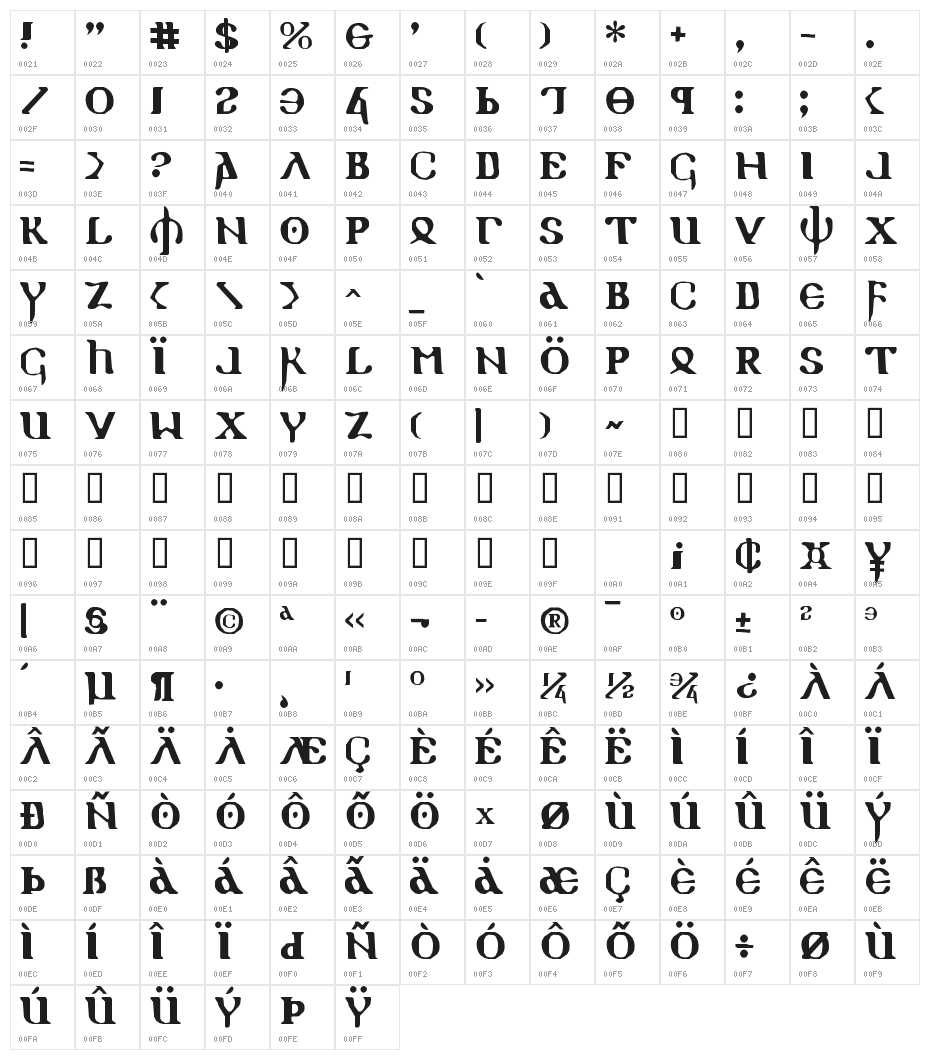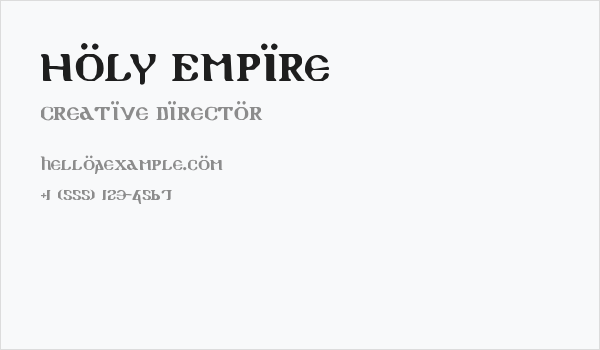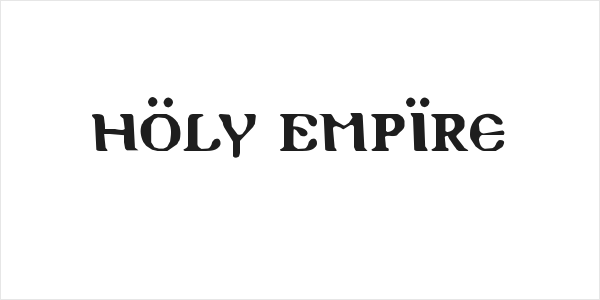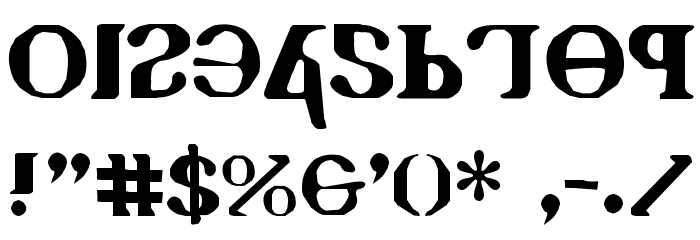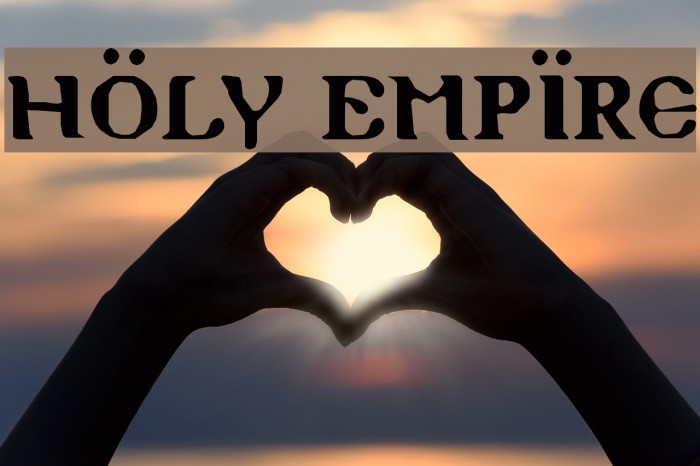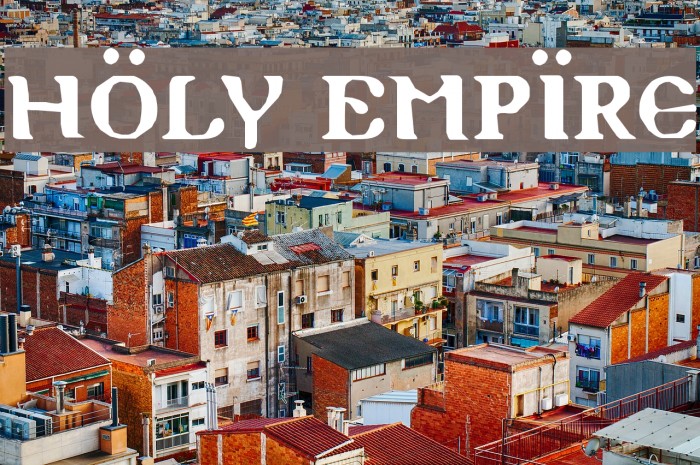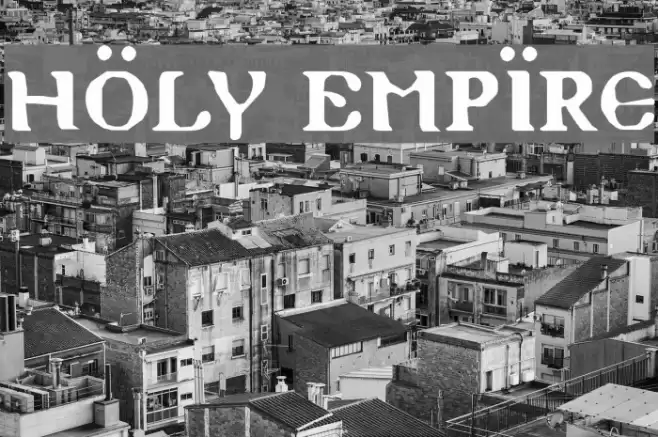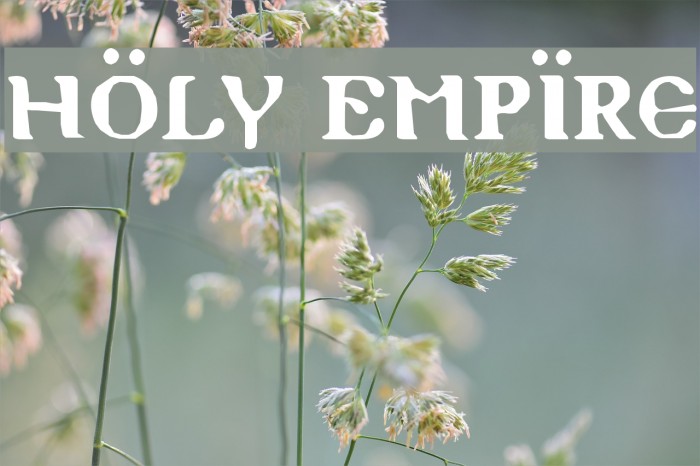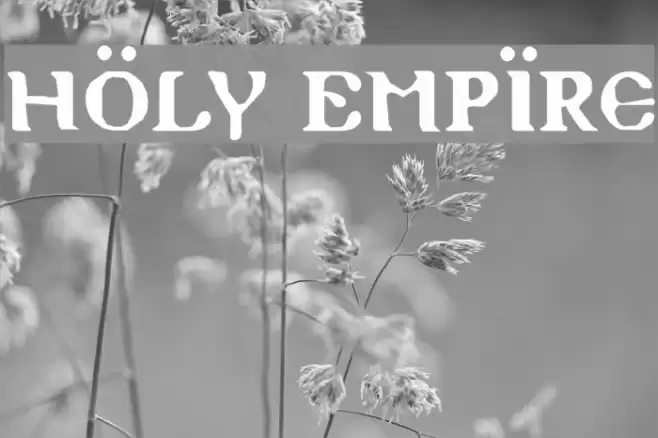
Holy Empire Font
| Cas d'utilisation | Headlines, Logos, Decorative text |
| Projets proposés | Ideal for use in historical themed projects, book covers, posters, and branding that requires a dramatic and authoritative look. |